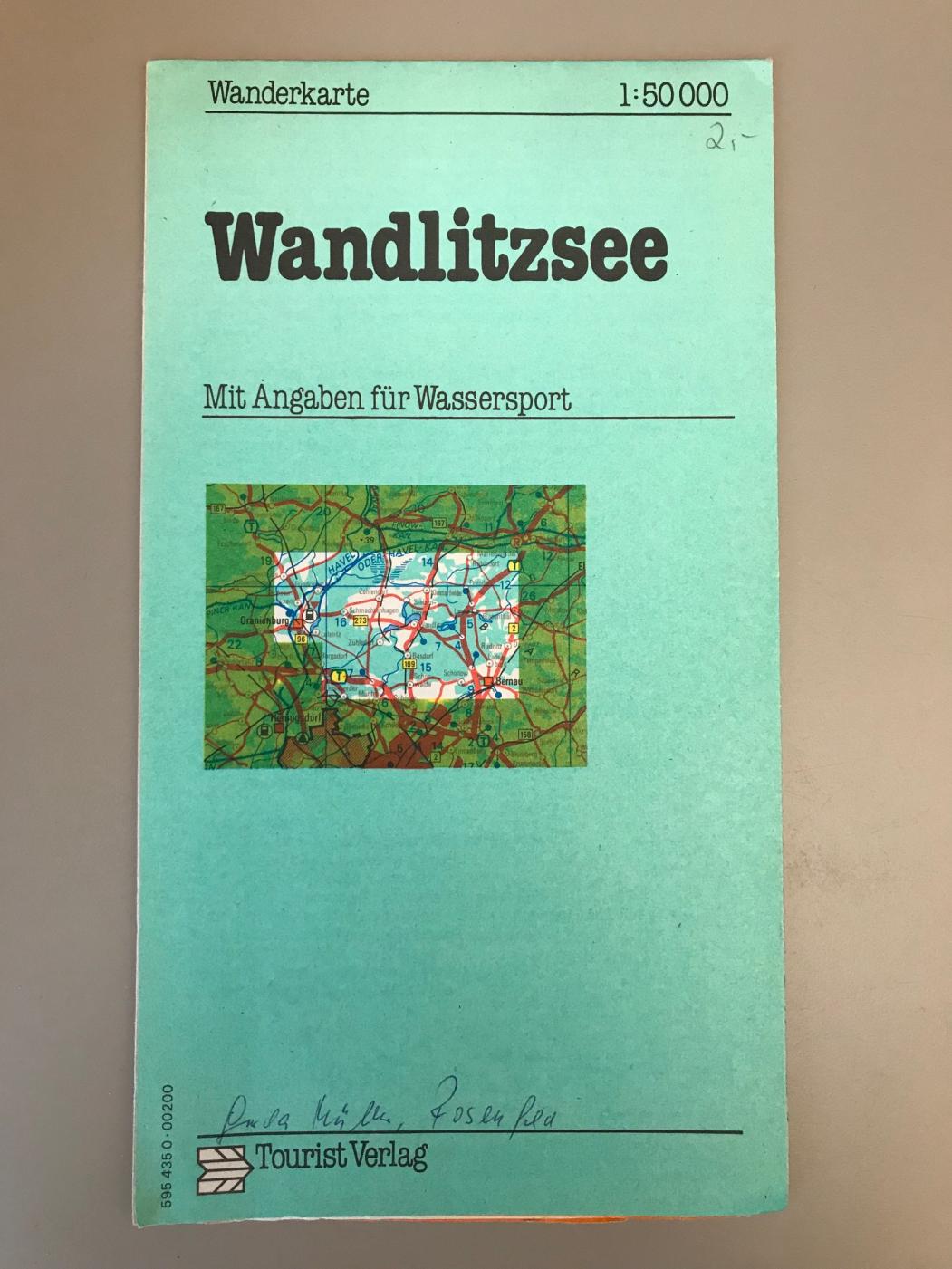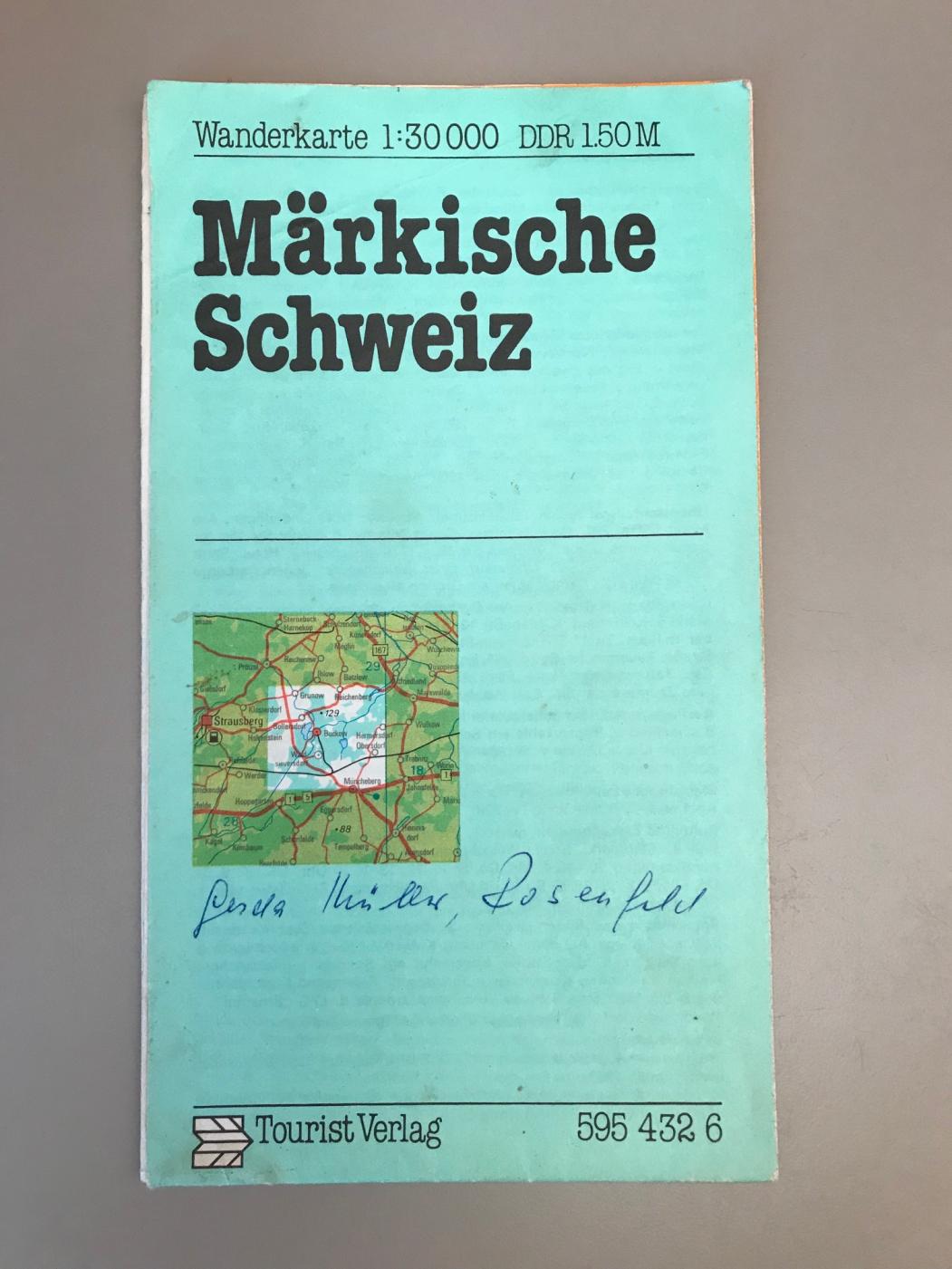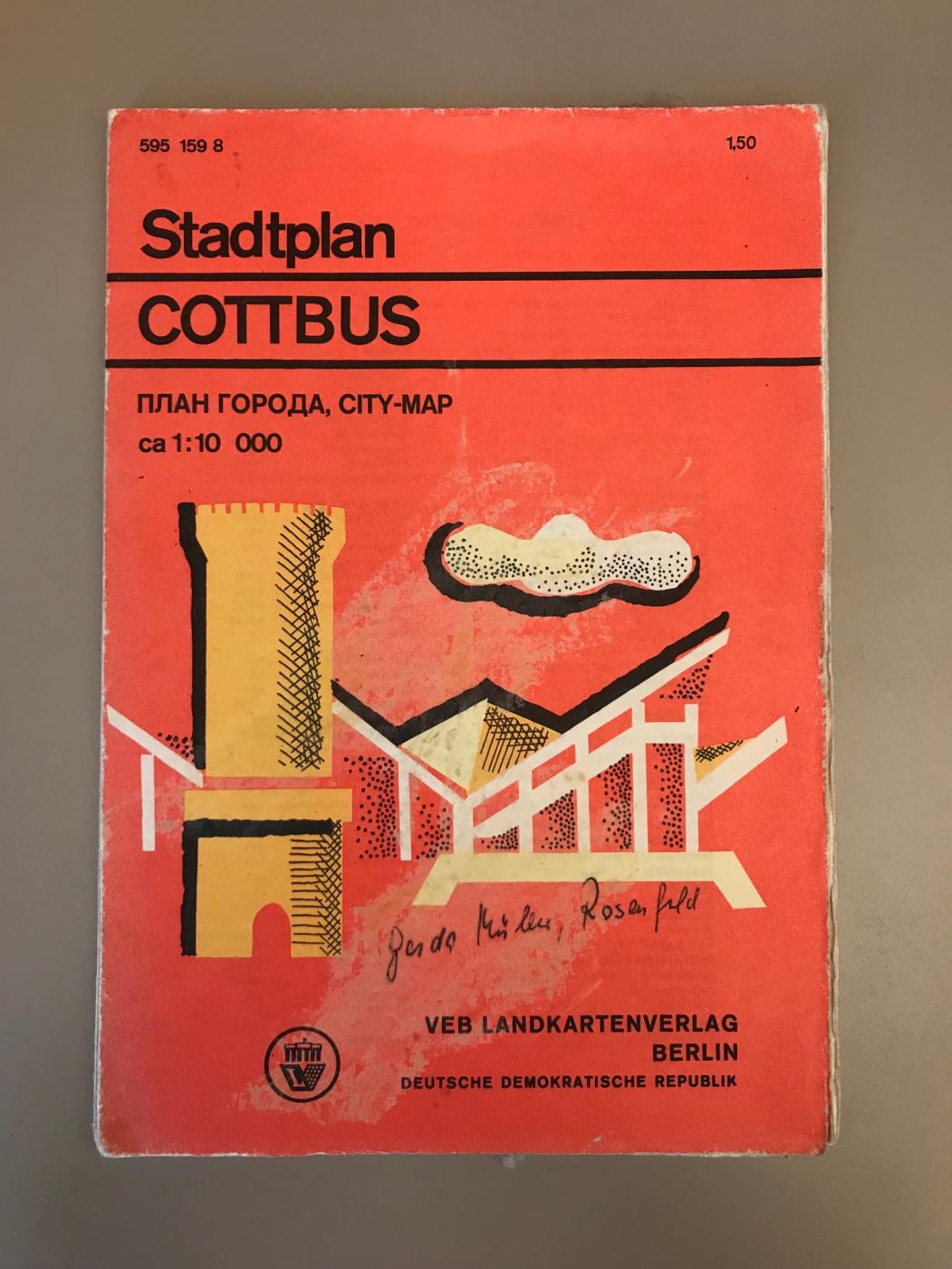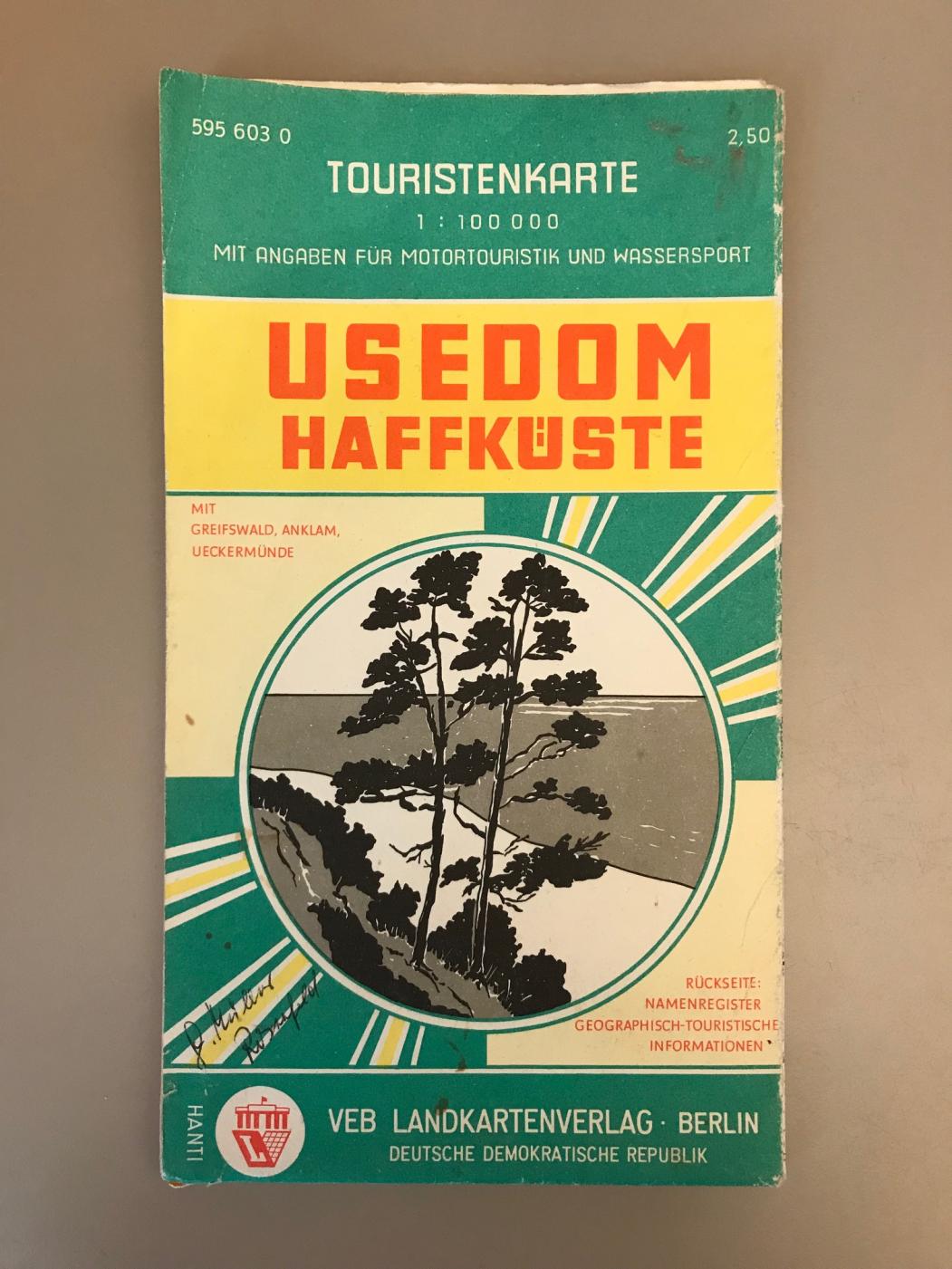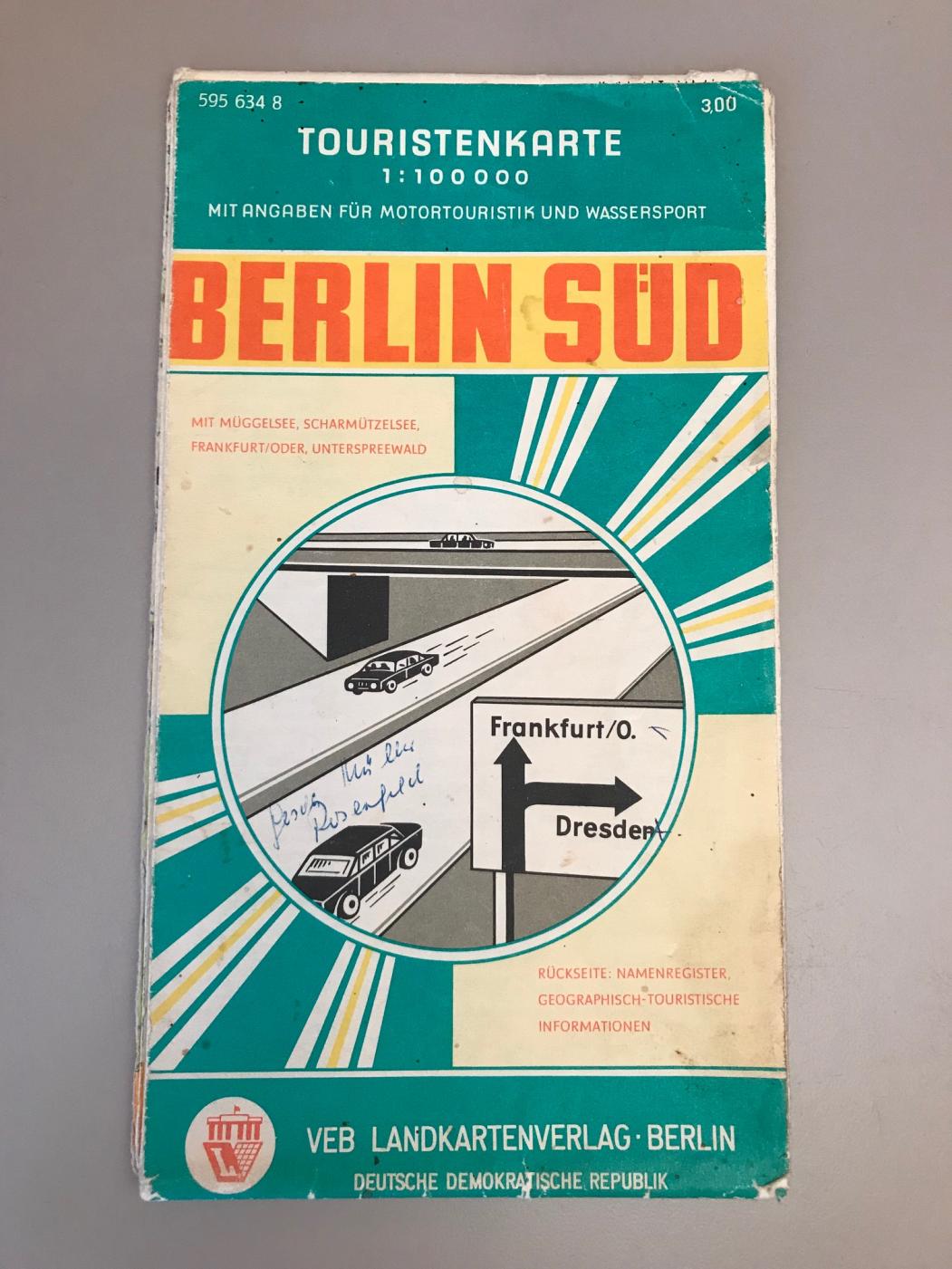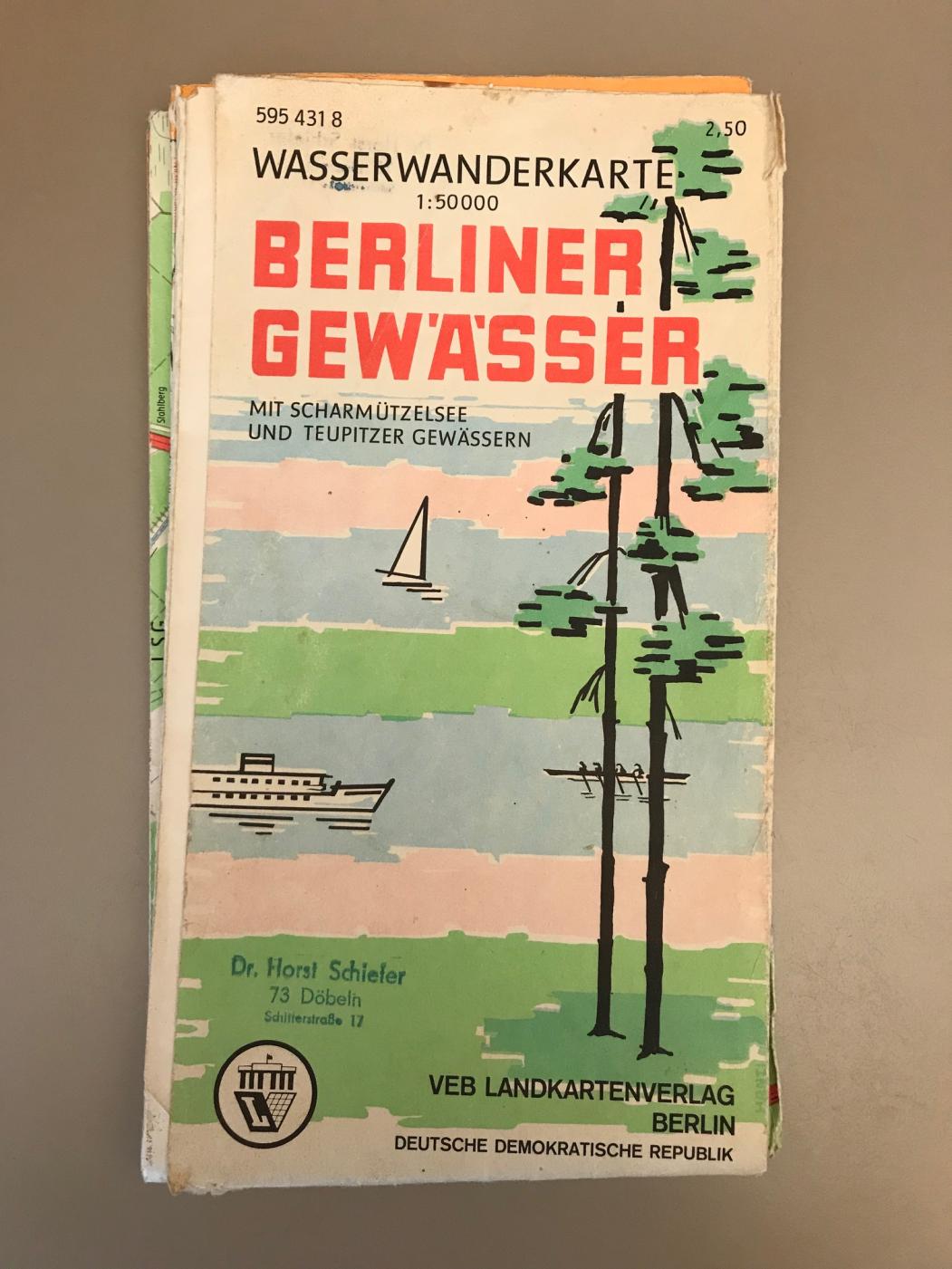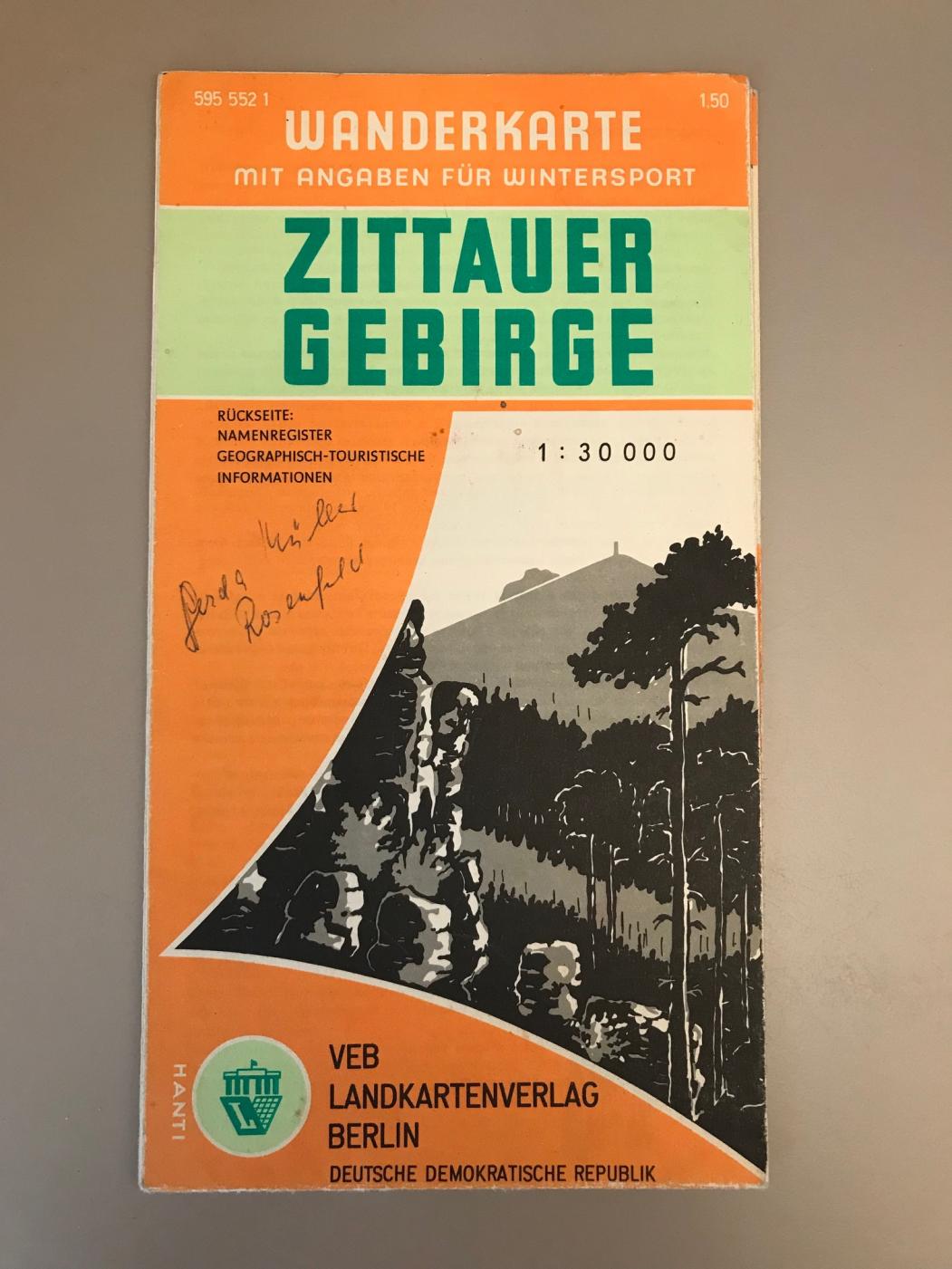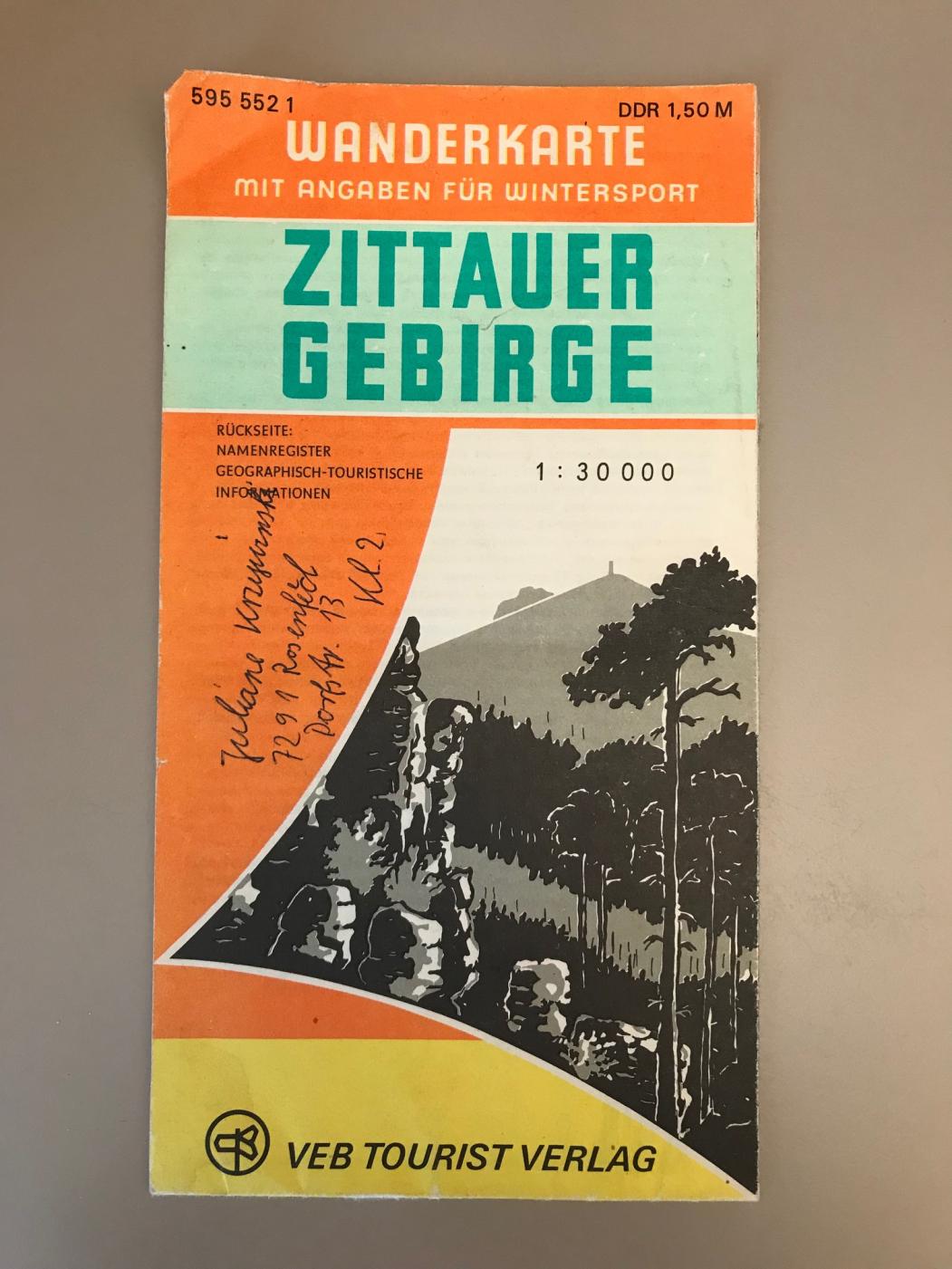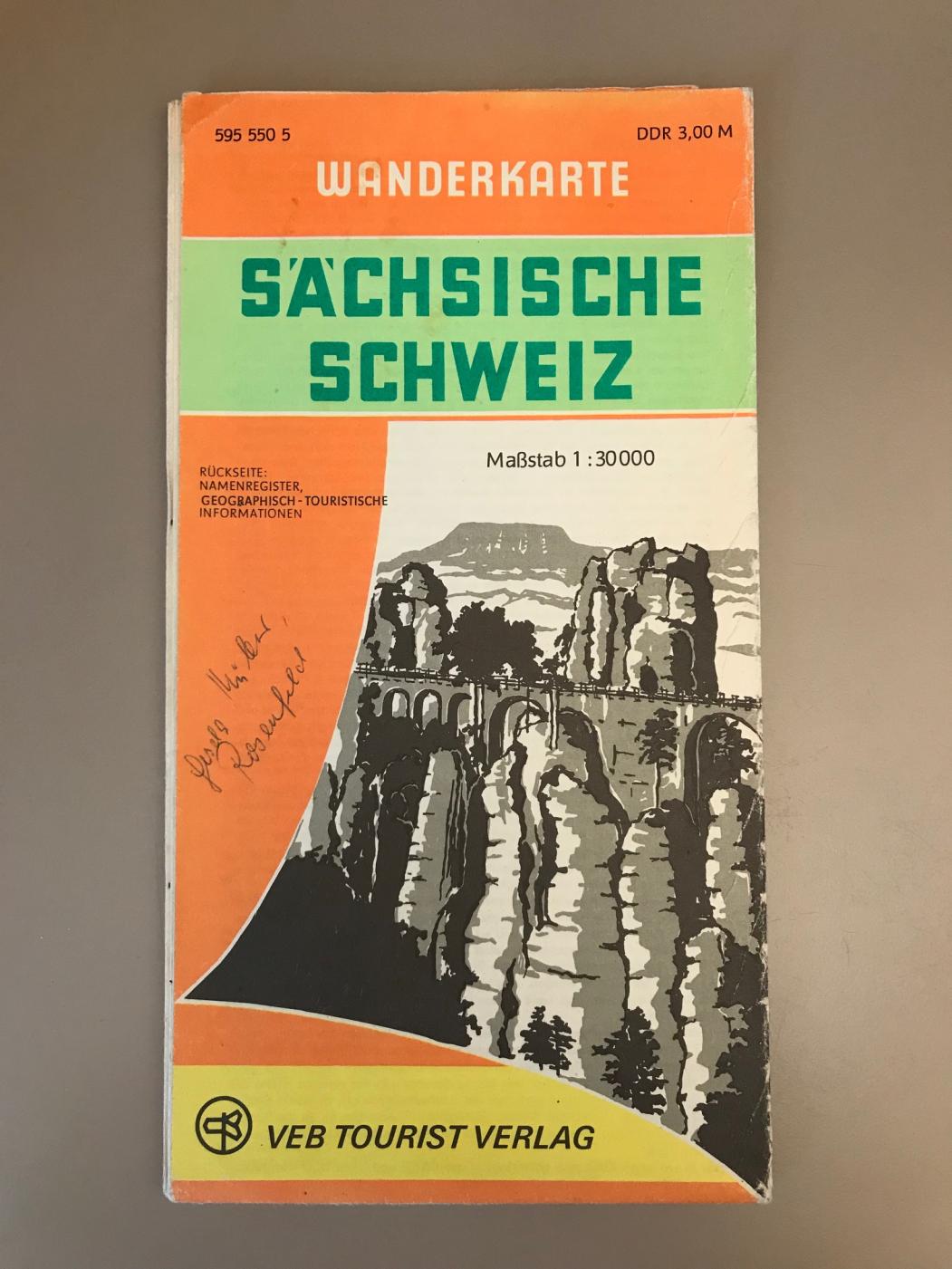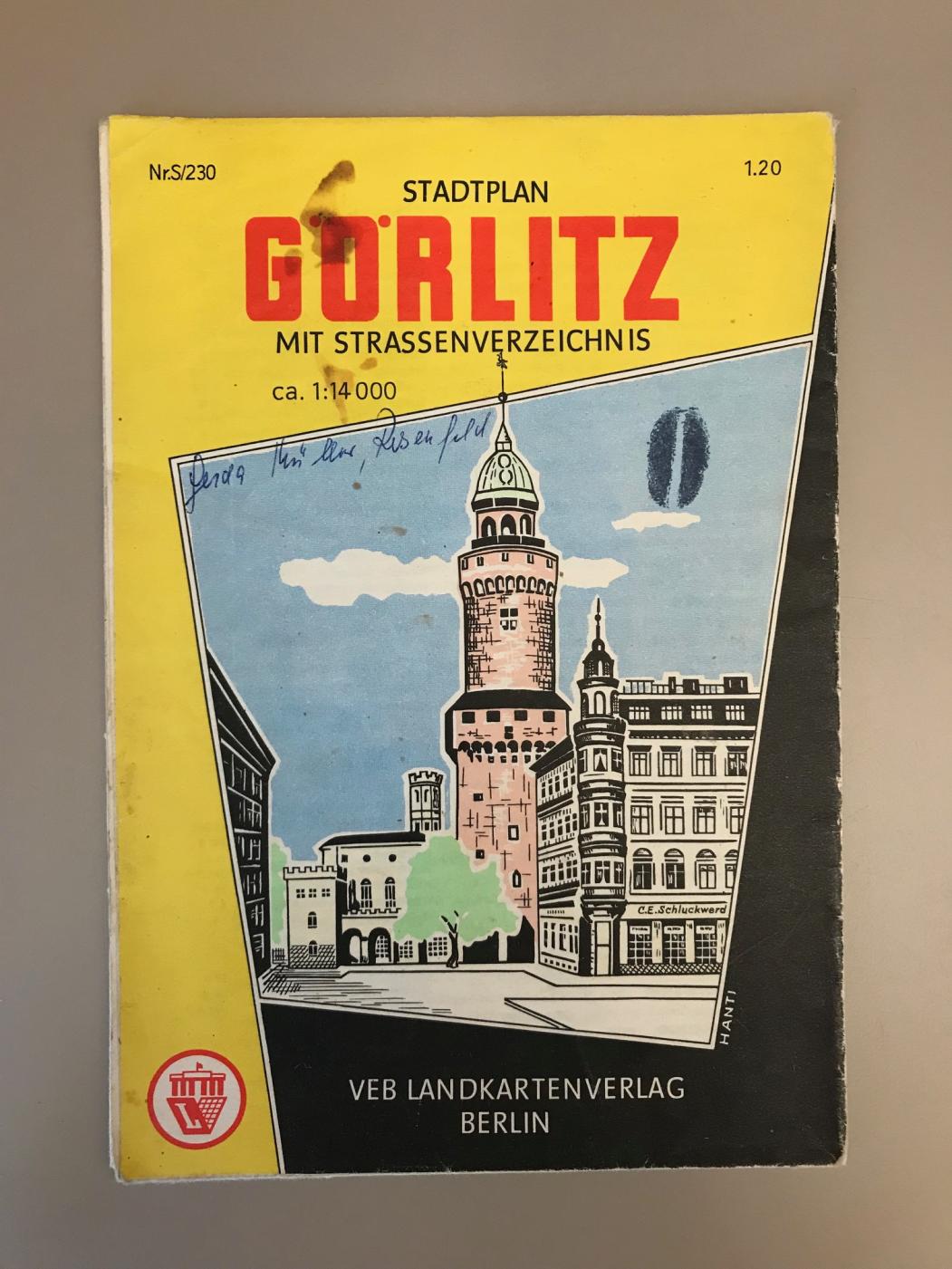
Meine Großmutter hat leidenschaftlich Landkarten und Reiseführer gesammelt. Gereist ist sie selbst eher selten - aber sie hat immer nachgeschaut wohin die anderen reisen. Am Wochenende ist mir ein Stapel mit alten Karten aus der DDR in die Hand gefallen. Die Deckblätter sind recht charmant und es gibt sehr hübsche Äs, Ös und Üs ...
Eine Rückseite in Schreibmaschinen-Schrift. Allerdings in ca. 6 Punkt ... wahrscheinlich getippt und später verkleinert. :shock:
Ganz tolle Bilder!